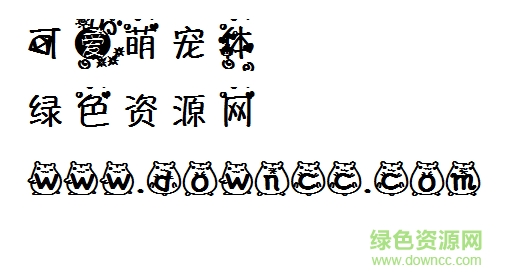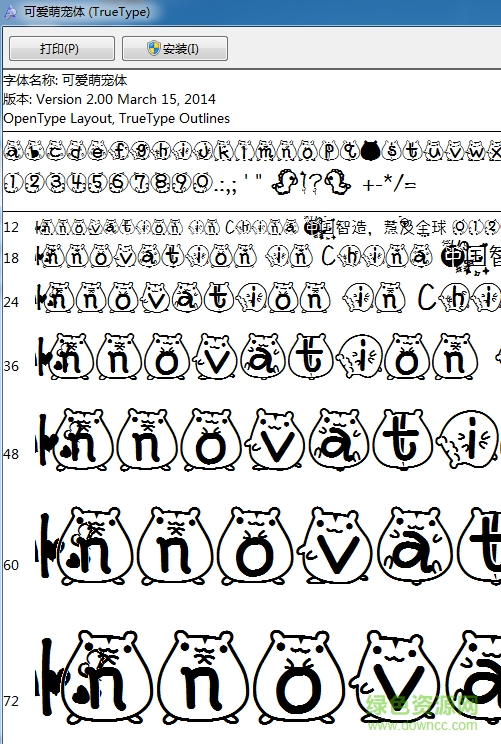
可愛萌寵體是一款萌系中文字體軟件,該字體有超多可愛卡通的圖案點(diǎn)綴,讓每一個(gè)字體都與眾不同,整體十分活潑好看,歡迎到綠色資源網(wǎng)下載使用!
可愛萌寵體字體造型生動(dòng)活潑,有鮮明的節(jié)奏韻律感,色彩豐富明快,給人以生機(jī)盎然的感受。這種個(gè)性的字體適用于兒童用品、運(yùn)動(dòng)休閑、時(shí)尚產(chǎn)品等主題。